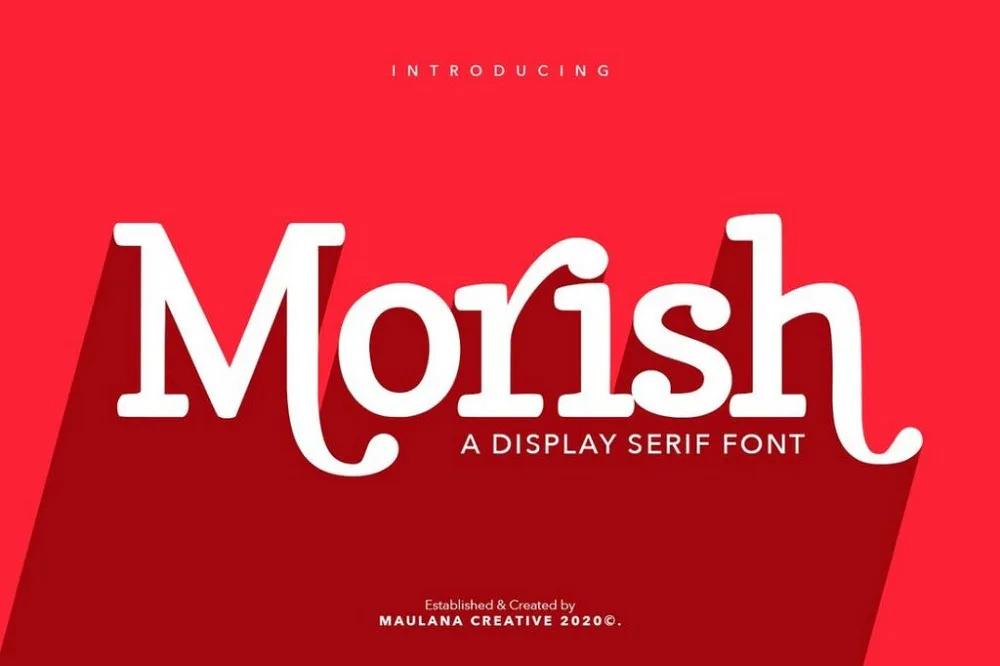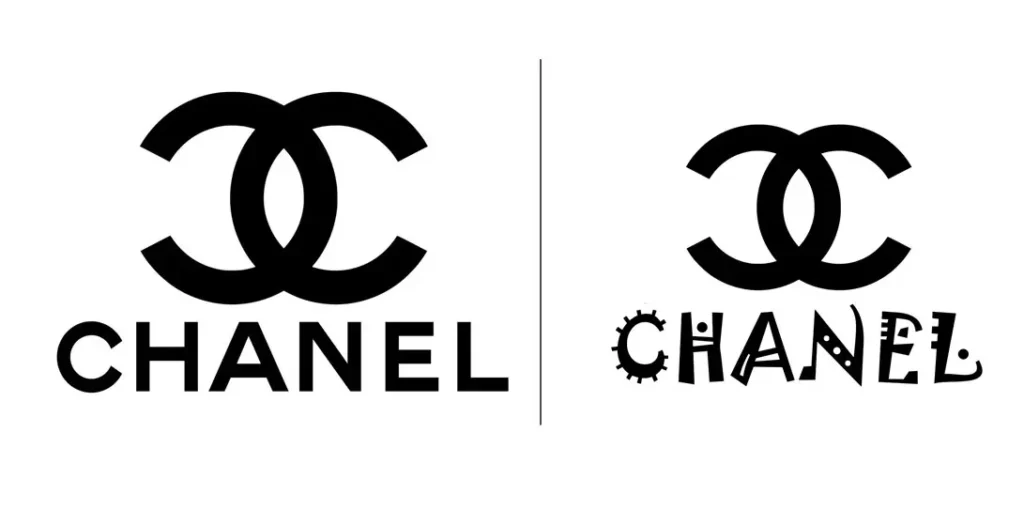
Tipografía en publicidad: la clave para un mensaje efectivo
La tipografía, a menudo subestimada, juega un papel crucial en el éxito de cualquier campaña publicitaria, tanto en medios impresos como digitales. Se trata del arte de crear y organizar el texto de manera visualmente atractiva y efectiva, capaz de captar la atención del lector y transmitir el mensaje con claridad.
Importancia de la Tipografía en la Publicidad
En un entorno saturado de publicidad, una tipografía bien elegida marca la diferencia. Influye directamente en cómo el público procesa la información, y una buena tipografía logra conectar con el consumidor a un nivel más profundo. Factores como el tipo de letra ( fuente ), el tamaño de letra ( punto ), el color y la longitud de las líneas son cruciales para asegurar la legibilidad y el atractivo visual.
Tipografía en la Publicidad Impresa
En la publicidad impresa, la tipografía es el vehículo principal del mensaje. Una tipografía efectiva tutorial al lector, destacando la información clave y facilitando su comprensión. Un buen ejemplo es un anuncio con un contraste alto entre el fondo y la letra, utilizando líneas cortas y un tamaño de letra impactante. La transparencia puede usarse para resaltar ciertas palabras o frases, creando un efecto de misterio o énfasis.
En contraste, una mala tipografía puede resultar confusa. El uso excesivo de diferentes fuentes, colores y alturas de línea, junto a una disposición desordenada del texto, dificulta la lectura y la comprensión del mensaje. La falta de jerarquía visual impide que el lector identifique la información más relevante.
Tipografía en la Publicidad Web
En el ámbito digital, la tipografía es fundamental para captar la atención del usuario en un tiempo limitado. Los sitios web disponen de apenas segundos para enganchar al visitante. Por ello, la estética del sitio, y en particular la tipografía, es crucial para una buena experiencia de usuario y para reducir la tasa de rebote.
La estructura jerárquica del texto, mediante el uso de etiquetas H1, H2, H3, etc., es esencial. Las etiquetas H1, con la mayor prioridad, deben contener las palabras clave más importantes y reflejar el tema principal. Las etiquetas H2, H3, etc., estructuran la información de manera lógica, facilitando la lectura y la indexación por los motores de búsqueda. El texto principal (etiquetas P) debe desarrollar la información con detalle y claridad.
Una buena tipografía web se caracteriza por su claridad, legibilidad y atractivo visual. El título debe ser prominente y fácil de encontrar. Los enlaces deben ser claros e intuitivos. El texto debe estar bien espaciado para facilitar la lectura y evitar la sensación de agobio.
Un mal uso de la tipografía web puede resultar en una alta tasa de rebote. El exceso de títulos, un diseño desordenado o un contenido superfluo pueden llevar a los usuarios a abandonar la página sin leerla. Es importante utilizar la negrita, la cursiva y el subrayado con moderación, para evitar la confusión y mantener la estética visual.
Ejemplos de Buena y Mala Tipografía
Selección de Fuentes
Una buena selección de fuentes garantiza la legibilidad y la armonía visual. Se deben evitar combinaciones confusas o poco contrastantes. Una mala selección puede dificultar la lectura y dar una imagen poco profesional.
Combinaciones de Colores
Las combinaciones de colores deben ser equilibradas y agradables a la vista. El exceso de colores puede distraer al lector. Un uso correcto del color realza el texto y mejora la experiencia de lectura.
Jerarquía Visual
Una buena jerarquía visual tutorial la lectura, destacando los elementos más importantes. Una jerarquía deficiente confunde al lector y dificulta la comprensión del mensaje.
Énfasis
El énfasis debe utilizarse con moderación para resaltar información clave. Un uso excesivo de negritas, cursivas o subrayados resulta confuso y contraproducente.
Altura de Línea
La altura de línea influye directamente en la legibilidad. Un espaciado adecuado entre líneas facilita la lectura y mejora la estética del texto.
Pautas para la Tipografía Corporativa
La coherencia en el uso de la tipografía es fundamental para la identidad corporativa. Es crucial desarrollar una tutorial de identidad corporativa que incluya las fuentes, tamaños, colores y otros aspectos tipográficos que se utilizarán en todos los medios. Esto asegura la consistencia y la profesionalidad de la imagen de la empresa.
Estas pautas deben incluir, como mínimo, el logotipo de la empresa, sus variaciones, las especificaciones de uso del logotipo (tamaño, espacio, etc.), la paleta de colores corporativa y las familias de fuentes. Se recomienda también incluir las especificaciones para la web, como la familia de fuentes, el tamaño y la altura de línea.
Consultas Habituales sobre Tipografía en Publicidad
La tipografía es un elemento fundamental en la publicidad. Una buena tipografía no solo mejora la estética, sino que también facilita la comprensión del mensaje, aumenta la efectividad de la campaña y crea una impresión positiva en el público objetivo. Utilizar las mejores prácticas en cuanto a selección de fuentes, colores, jerarquía y altura de línea es clave para el éxito de cualquier estrategia publicitaria.